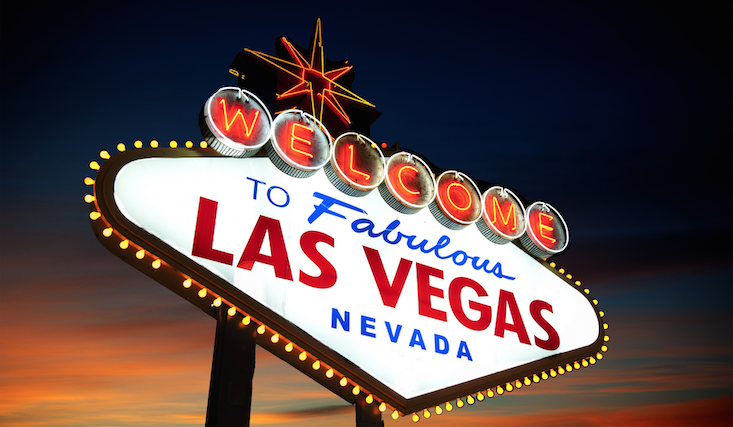
La tipografía forma parte del paisaje. Sobre todo hoy en día, época en la que las ciudades, regiones y países se han convertido también en marcas. Logotipos y letras propias son elementos que identifican una ciudad, un autor y también una marca. ¿Por qué será?
Porque la tipografía evoca sentimientos, valores y costumbres. De hecho, una de las funciones de la tipografía es marcar el tono de lo que estamos leyendo. Así lo explica Pixartprinting en “Sentir la tipografía”, donde hace un recorrido por los sentimientos evocados por los tipos de letra.
Y es que la tipografía unifica la comunicación de las instituciones locales y, aunque sea de manera subconsciente, nos ayuda a reconocer una imagen homogénea de los lugares, personas e instituciones. De hecho, se suele decir que si nos dejasen caer con los ojos cerrados en medio de una ciudad seríamos capaces de reconocerla simplemente mirando sus rótulos y señales.
Un ejemplo de ello puede ser el metro de Berlín, en el que se mezclan modelos tipográficos de lo más dispares: desde rótulos neoclasicistas de 1913 hasta otros con tipos setenteros:
También Francia, conocida por su tipografía redondeada y ornamentada:
O Viena, donde la cursiva ya es un elemento característico:
Bruselas incluso unifica la misma tipografía en cualquier soporte, móvil o estático:
Los ejemplos son tan numerosos como tipografías existen en el mundo.
De vehículo a evocadora de emociones
Sin embargo, las emociones que los tipos de letra nos evocan no se limitan a la simple identificación de lugares o marcas. La asociación trabaja a un nivel subconsciente, influyendo en nuestros sentimientos e impresiones sobre lo que estamos leyendo, independientemente del contenido.
Un ejemplo de esta asociación son los tipos romanos tradicionales. El tipo Times New Roman lo tenemos asociado a periódicos serios, así que al leer cualquier texto en el que se utiliza esta tipografía tenemos la sensación de estar leyendo algo riguroso y creíble. Es el lado opuesto a Comic Sans, el terror de cualquier diseñador gráfico.
El ser humano es sensible y su historia comienza cuando se crea la escritura. Es por eso que la tipografía siempre nos afectará en mayor o menor medida, incluso llegando a identificarnos con un tipo de letra concreto (ya sea porque es la que usa la marca favorita de un consumidor, o el libro favorito de un lector).
Manuel Sesma, doctor en Bellas Artes y escritor del libro Tipografismo, afirma al respecto: “somos capaces de percibir más utilidades tipográficas de las que pensamos, y sólo necesitamos fijarnos más en nuestro contexto tipográfico. Es fácil. Vivimos dentro de un gran libro”.